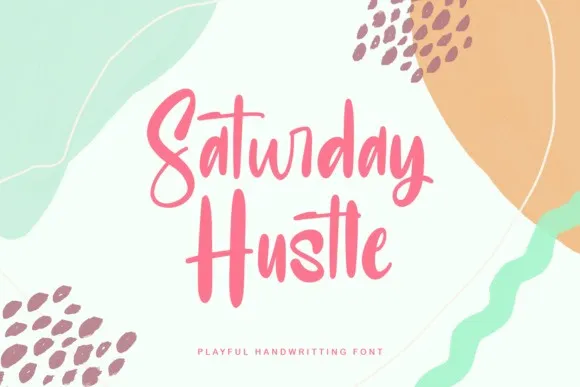
A Saturday Hustle Font é uma elegante escolha para designers que procuram um estilo casual mas profissional. Com seu traço limpo e marcante, esta fonte script atinge a perfeição entre simplicidade e exuberância. Disponível com as características de tipografia avançadas como alternâncias estilísticas, conjuntos estilísticos e ligaturas para uso em logotipos, panfletos, badges, capas de livros, camisetas e embalagens, entre outras criações. Esta fonte é perfeita para qualquer design que busque um toque único e criativo, tornando-a uma ótima opção para quem quer dar ao seu projeto um visual distintivo.